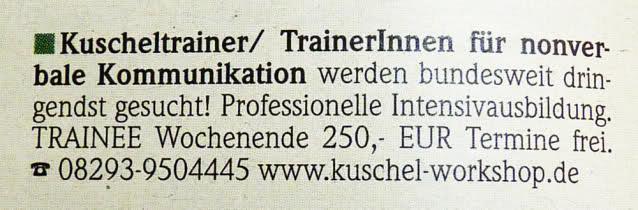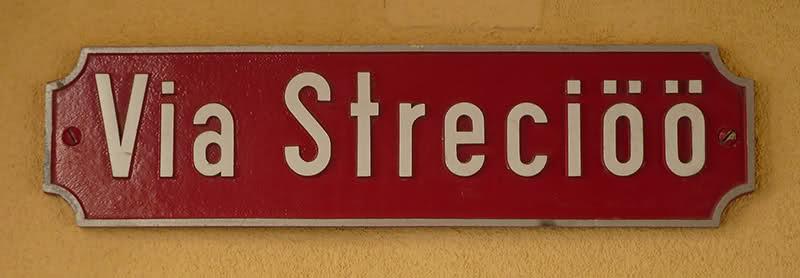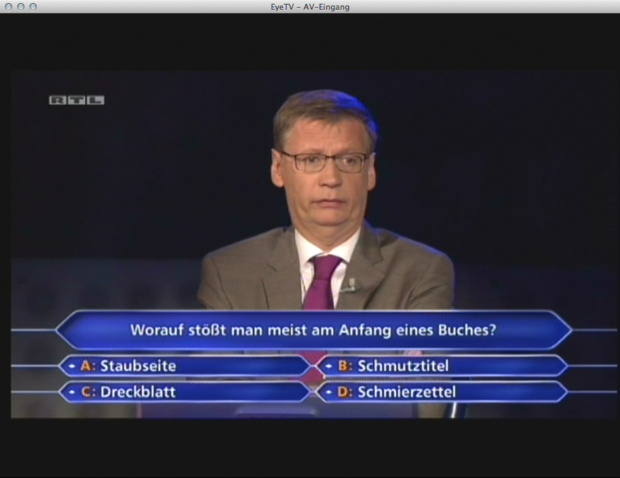
Na ja, die brauchten halt genug Platz für die Sessel. ;-) Wir sollten vermutlich dankbar sein, dass sie die Buchstaben nicht gestapelt haben … Vielleicht wurde aber auch nur kurz vor der Sendung die Bühne noch mal feucht durchgewischt und keiner hat daran gedacht, alles wieder an seinen alten Platz zu schieben …
ich glaub ralf wollte eher zeigen das das A verkehrt aufgeklebt wurde.
horizontal gespiegelt. wobei ich mich frage wie sowas passieren kann.
Jepp. Aber in diesem Kreise sollte das jeder sofort sehen. Daher hab ich da nicht extra drauf hingewiesen. ;-)
Ich oute mich hiermit: hab es nicht sofort gesehen. Nur: irgendwas stimmt hier nicht.
Frisch aus dem Tessin:
Eher ein Stierhorn als ein Apostroph …
Und Ungewohntes in Rätoromanisch …
geld gab es, weiss aber nicht mehr wieviel. war aber noch im unteren bereich.
der kandidat wusste es nicht, der telefonjoker wusste es gerade so, weshalb der
kandidat seine antwort nochmals mit dem 50:50-joker abgesichert hat und zum
schluss somit die richtige antwort gewählt hat.
Kuscheltrainer ist schon klasse, wa?
Dringendst gesucht ...! Das wusste ich noch nicht.
Aber Trainer und TrainerInnen - da frag ich mich doch, wer damit alles gemeint ist?!
Fühlt sich jemand angesprochen?